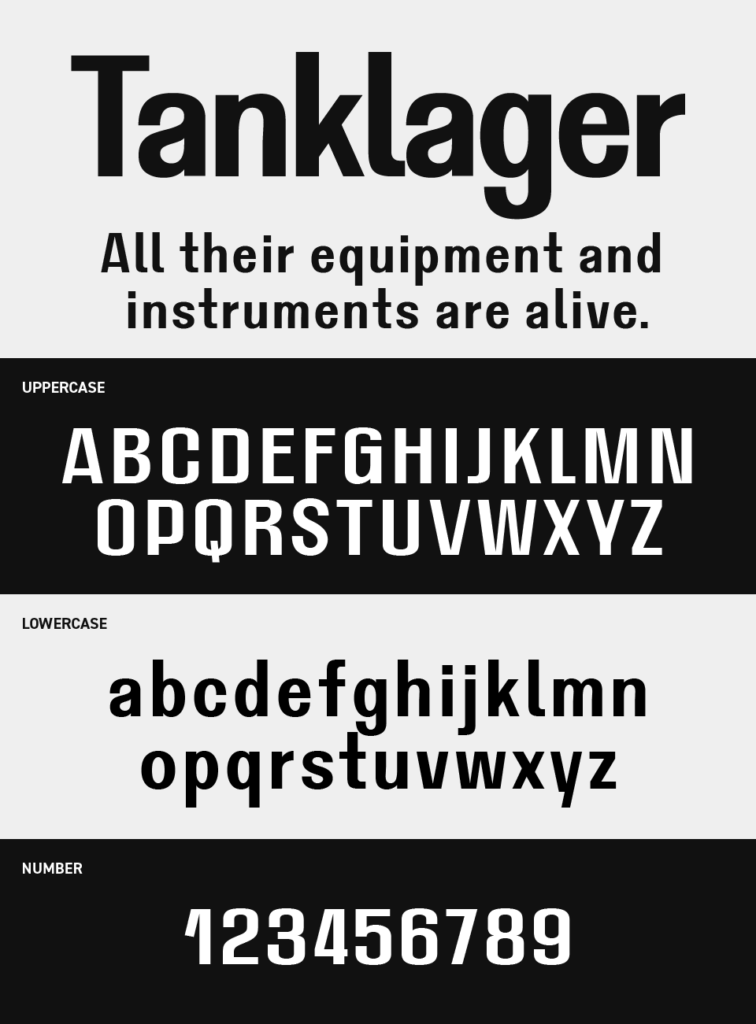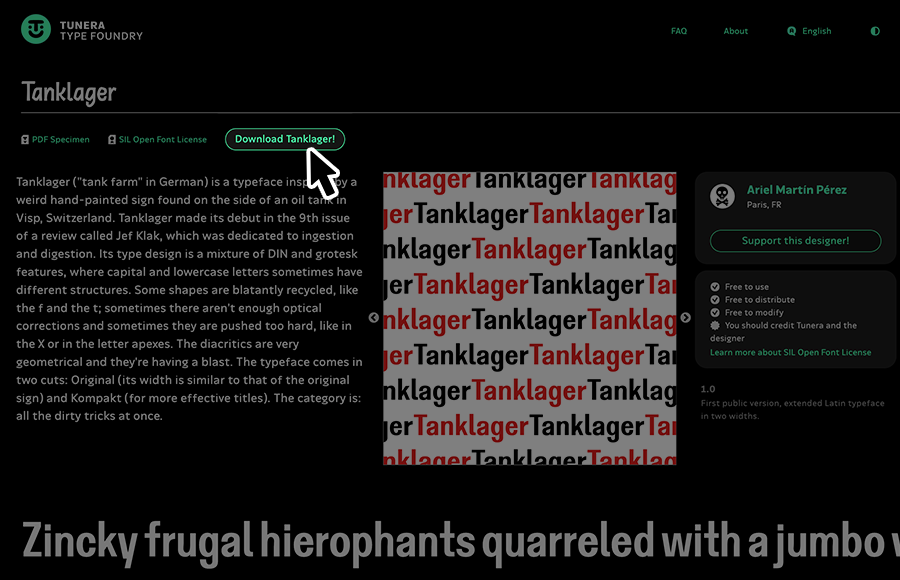
Tanklagerフォントは、無駄を削ぎ落としたシンプルなサンセリフ体で、どっしりとした安定感のあるサンセリフ体フォントです。
石油タンクの側面に描かれた奇妙な手書きからインスピレーションを得て制作されたということで、少し工業ちっくさを感じさせられるかっこいいフォントとなっています。
クセが強すぎないため他のデザイン要素とも調和しやすく、モダンで落ち着いた雰囲気をつくれるフォントです。